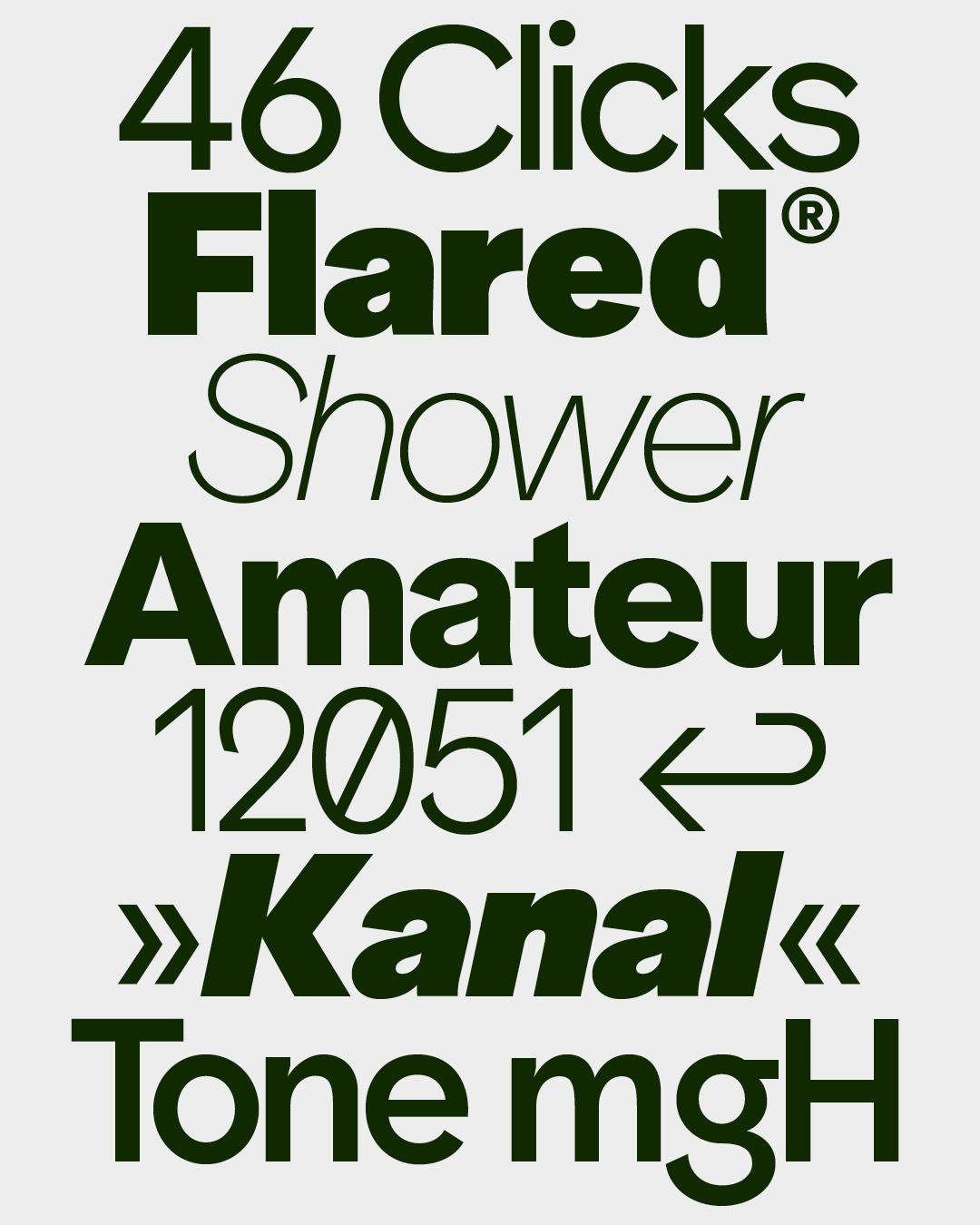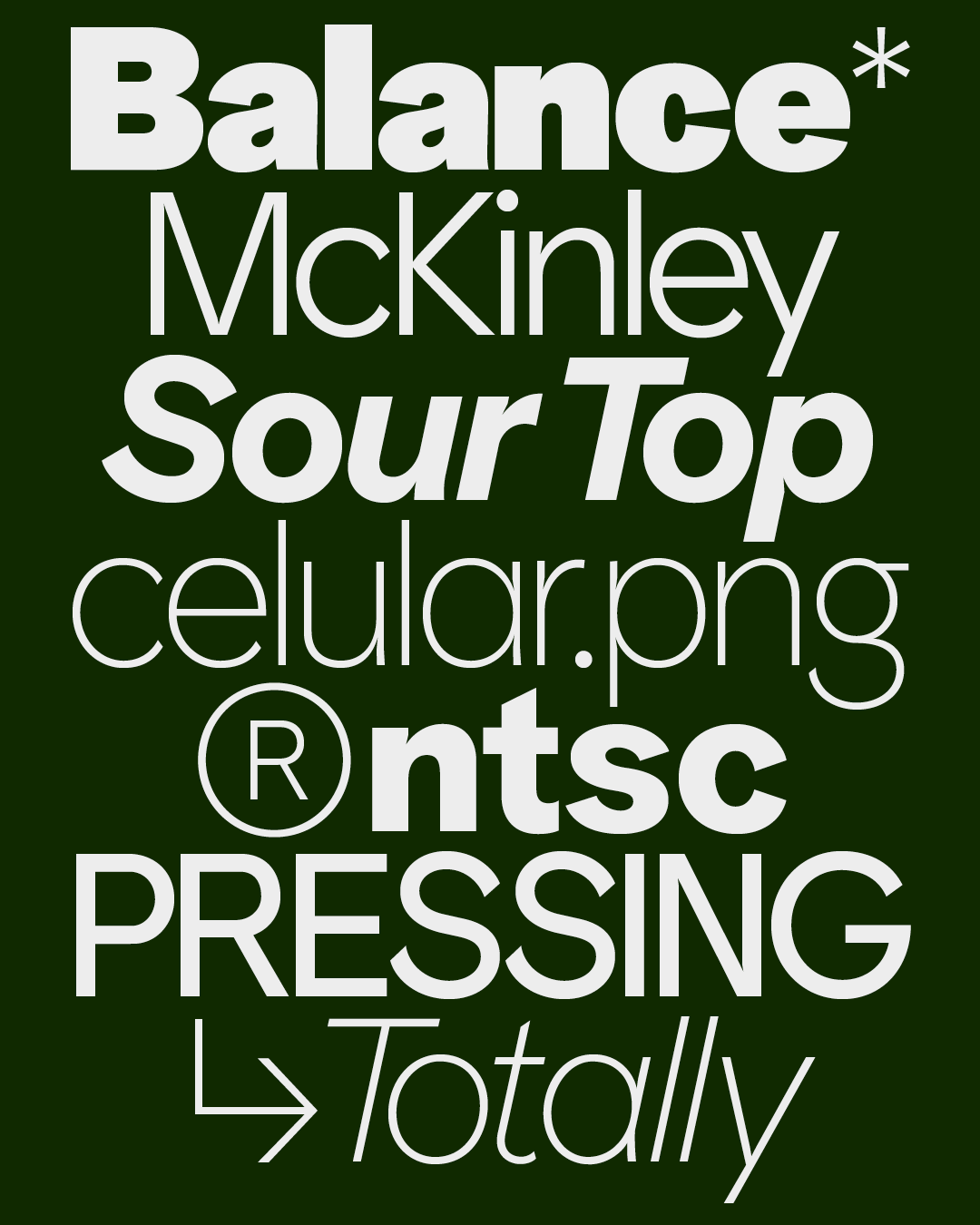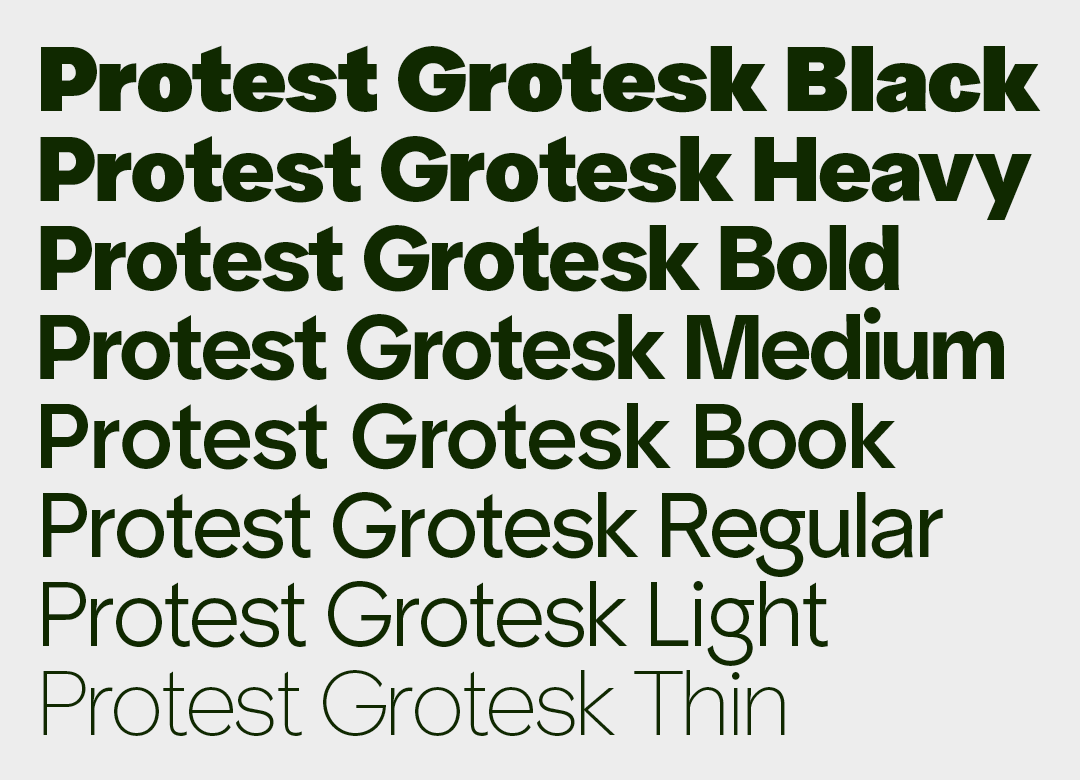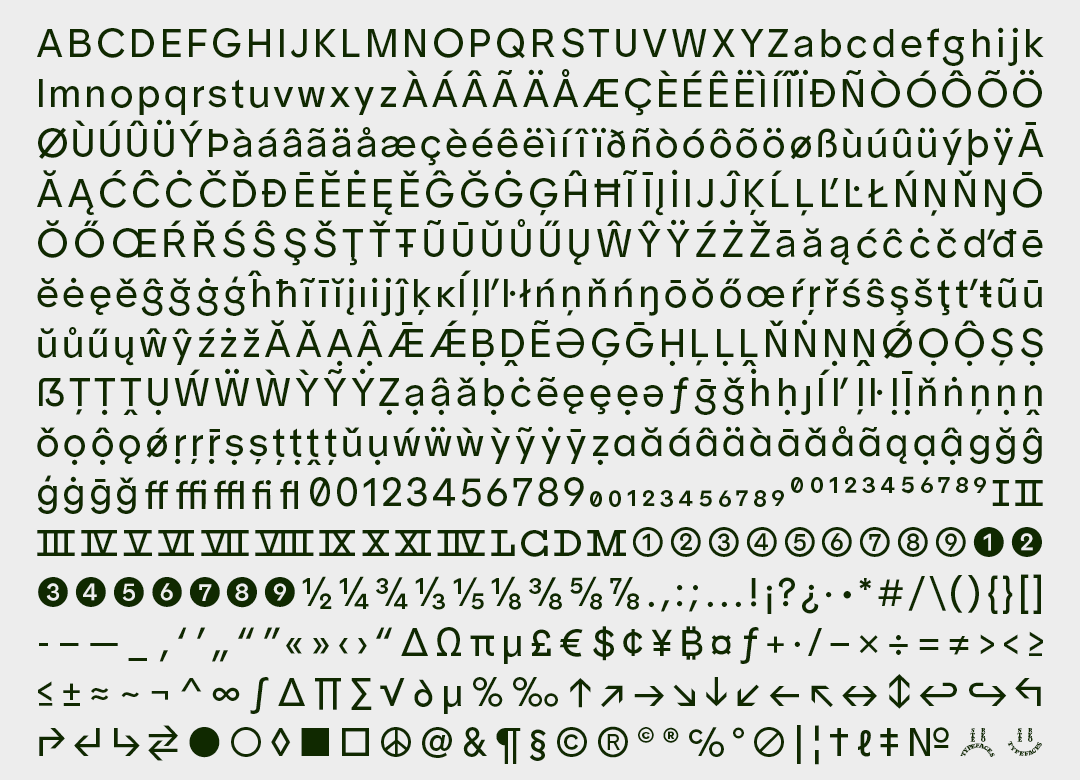
Protest Grotesk ist eine serifenlose Schriftfamilie der Berliner Type Foundry Softdrive. Es handelt sich um eine geometrische Sans-Serif die auf den Einsatz im Mengentext optimiert ist. Die Schrift liegt aktuell in 8 Schnitten mit jeweiligen Italic-Varianten vor.